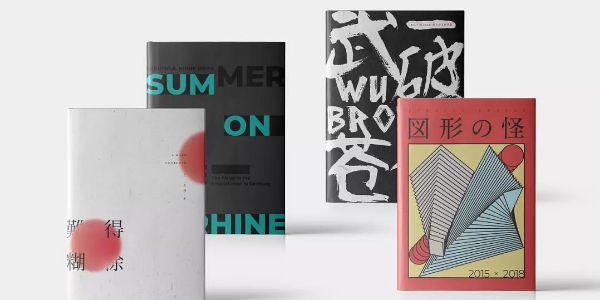
如何让logo、海报设计更有内涵,来看看这篇干货
今天柚子来说说汉字的图形化,一听到这个,就觉得很深奥,跟自己没啥关系吧?
大错特错,你做logo、海报设计的时候,字体是拿来就用吗,不得变个形,加个特效,恨不得成为你专属的符号啊!
不过今天我说的更高级,是把汉字的“意”和“形”相结合,一个代表文字的含义,一个代表含义的想象力,双剑合璧,才能爆发艺术的生命力。
最早的文字什么样
在还没有文字的时候,其实都是以图画和象形文字来表现的,我们的祖先又没有手机可以拍照,只能用贝壳、结绳、刻绘符号来记载他们的生活,而这些就是图画文字。
到我们最熟悉的甲骨文,应该算是发展比较完整的阶段了。
像日、月、山、水、草、木、鱼、鸟等,就是经过古人精心刻画的象形文字,虽不像现在的汉字那么规整,但已经具备了一些方块字的感觉。
经过几千年的演变,甲骨文变成了简单的字体,而今天,我们又追溯历史,在古文字的基础上,创造了“图形化的文字”,真是很轮回。
这些你一定很熟悉
一说古代文字,就不得不提到书法了,之前在金庸“归隐”,可他的书法江湖还在流传也说过,它是最精粹、最受尊崇的艺术形式之一。只要以毛笔为工具,用气韵挥洒线条,就能表现出生动的图形感。
而篆刻,在书法的基础上又升级了,笔画匀称、似字似画,可谓是汉字图形化的领军人物。现在很多品牌的logo,都喜欢用印章的形式,比如我周一刚发的《神奇动物2》的这些细节,你真的看懂了吗?
一般分三种,小篆的特点是比较柔婉、结构严谨;殳篆的装饰味道比较浓,常用在古代的兵器上;而宋元时期的“九叠篆”,以笔画盘叠出名,最多能达到十篆。平时可以多研究它们的规律,毕竟每一种都将汉字图形化发挥到了极致,会给设计带来超多灵感哦。
如果你觉得书法、篆刻还离你有点远,那下面这个“囍”不陌生了吧?只是为了“喜事成双”的美好愿望,就把它图形化了,毕竟字典里是查不到这个字的。
还有这个很常见的“千寿图”,每一个寿字的笔划都精心设计过,放在一起就能营造出欢乐吉祥的气氛。
logo中的运用
了解了汉字图形化的发展演变,接下来我们来看看它怎么跟标志结合。
从古至今,很多商标,都是以人名、地名、店铺名,直接命名的。
比如北京大学的篆字校徽,就是一款经典的文字图形化的作品,鲁迅先生设计的。
如果我们把汉字和一些现代的手法结合,就能在传统文化底蕴的基础上,设计出符合现代审美的作品,一起来设计几款logo吧!
先要找一款优质的字体做参照,上来就自己乱画,那骨骼肯定是控制不好的,我选择思源黑体(字由上能搜到)。
把大致的结构搭建出来,在基本形态之上进行变化。
新字体的骨架搭建好了以后,还需要对他进行细化。中间菱形的处理方式,参照了一款古代的篆刻,笔画之间的间距,则是运用了1:1.414的白银比例,倾斜线条的角度为45度。
如果想增加一些历史感,还可以把笔画交界处,处理成圆角,这样一款图形化的字体就设计好了。
除了这款图形化的logo,还可以有其他几种形式。比如这款,笔画都使用了圆角,有点卡通的感觉,比较适合年轻的品牌。
还有这种,从第一款案例中延伸出来的,把茶字嵌在茶叶的形里。
这款更像印章、剪纸的感觉,比较简单、日常。
第一眼看到这款,估计你已经认不出文字了吧?只是根据前面几款的变化,还能找到些许影子(往下拉,它还有用武之地)。
最后来张全家福,还是很有意思的,加上文字,就可以作为logo使用了,当然了,不加也没问题。
logo的图形和文字,是一个整体,可以相互完善、彼此补充。所以也不用纠结它是否抽象,只要简单、好记就足够了。
海报中的运用
如果从汉字到logo还比较直观的话,那么海报就更考验想象力、装饰感和视觉张力了。
世界上很多设计师,都喜欢研究各种形态的汉字,比如日本设计师白木樟的作品。
还有香港设计师靳埭强的作品,他们都是依据主题或者设计需要,对海报赋予了汉字的灵魂。
可以说,汉字图形化已经成为当今平面设计的一种主流了,观者既容易理解文字内涵和主题,又会被这种感染力所吸引。
形式一般包括两种,一种是单字的图形化,还有一种是多字的图形化。
举个栗子,下面这两张海报,就是单字图形化。左边红色标记的地方,就是把完整的汉字拆分,再通过叠加、调整大小、改变颜色,重新设计而成。而右边则是把单个的字,与插画结合在一起。
多个汉字组合而成的图形化,就是下面这种,把文字打包在一起,整体进行变化。
还有一种表现手法,就是分解重构,把原来的形象,进行打散、切分,再根据设计需要,从不同的角度进行重组,具有强烈的艺术表现力。
下面依然是实操演练,主题就不换了,还是关于茶叶的,先搭好骨架。
这回我们要替换笔画,把草字头的两点,和下面的撇和捺,换成茶叶。但要注意,尽量不要动主笔画,这样相对好控制。
整体是汉字茶,填充的叶子即是茶叶,又像人的眼睛,可以代表展示这个概念,算是比较容易理解的设计。
主体有了,下面我们继续给海报添加文字,左面是海报需要的标题、时间、地点、主办单位等信息。
由于主体两边太空,所以把标题的英文作为装饰元素,放了进去,还在右下角,把之前做的亲妈都认不出的小logo放进去了(梗在这里),是不是整体就平衡了。